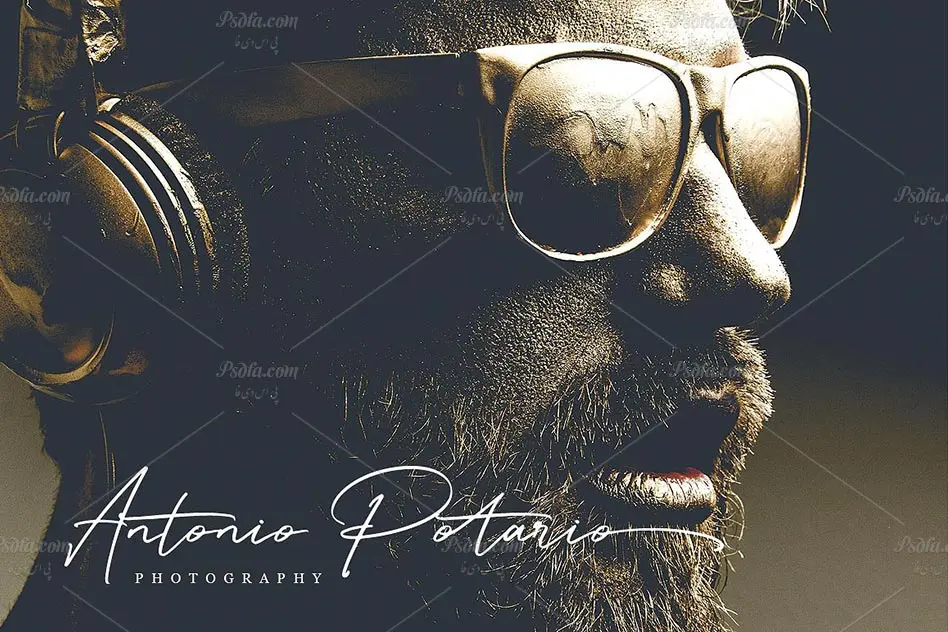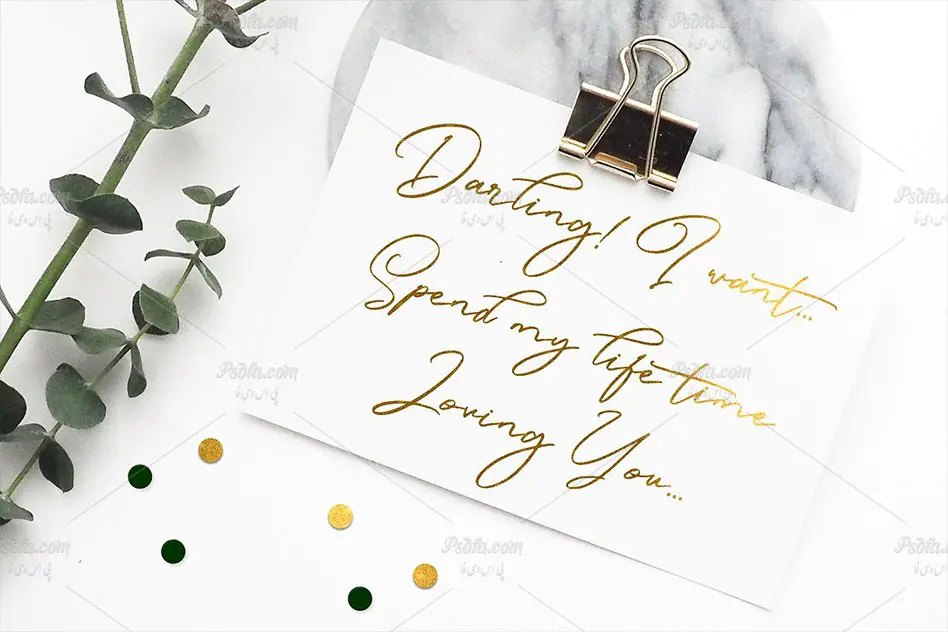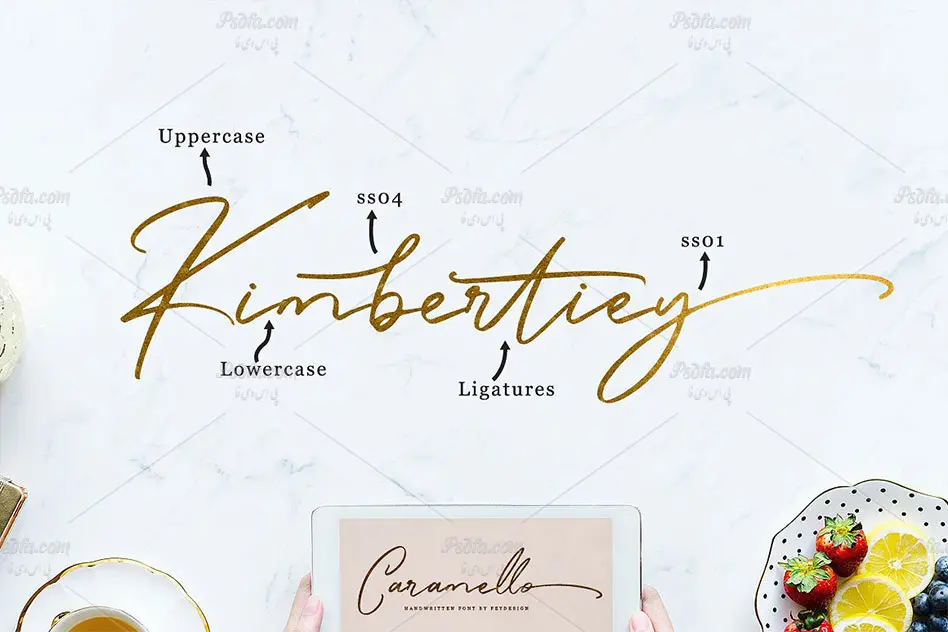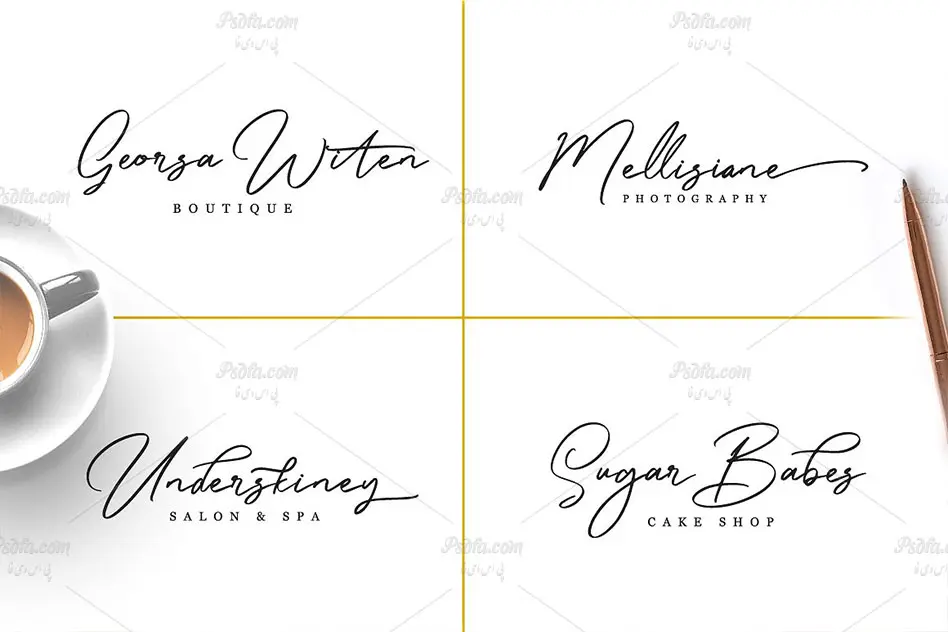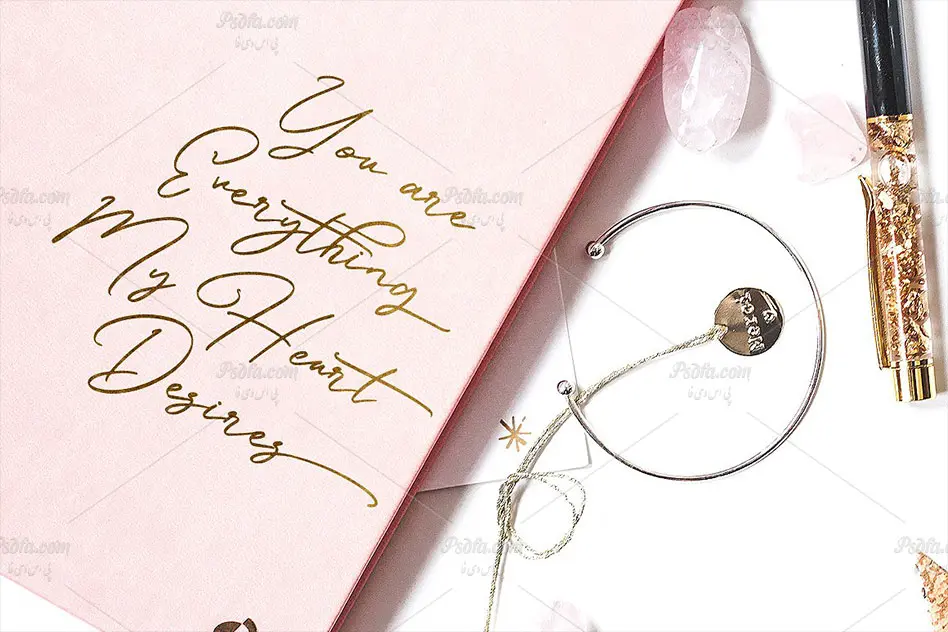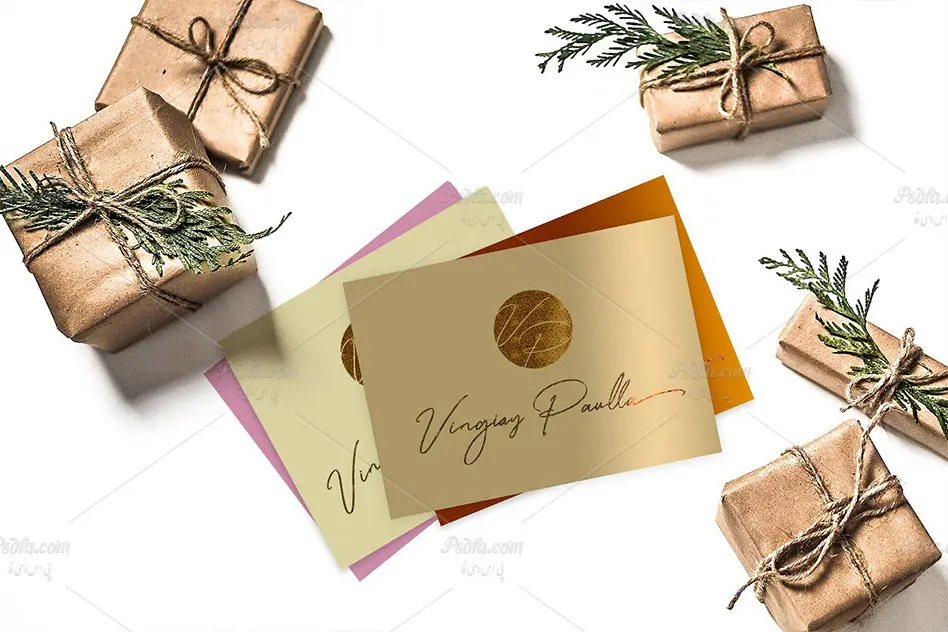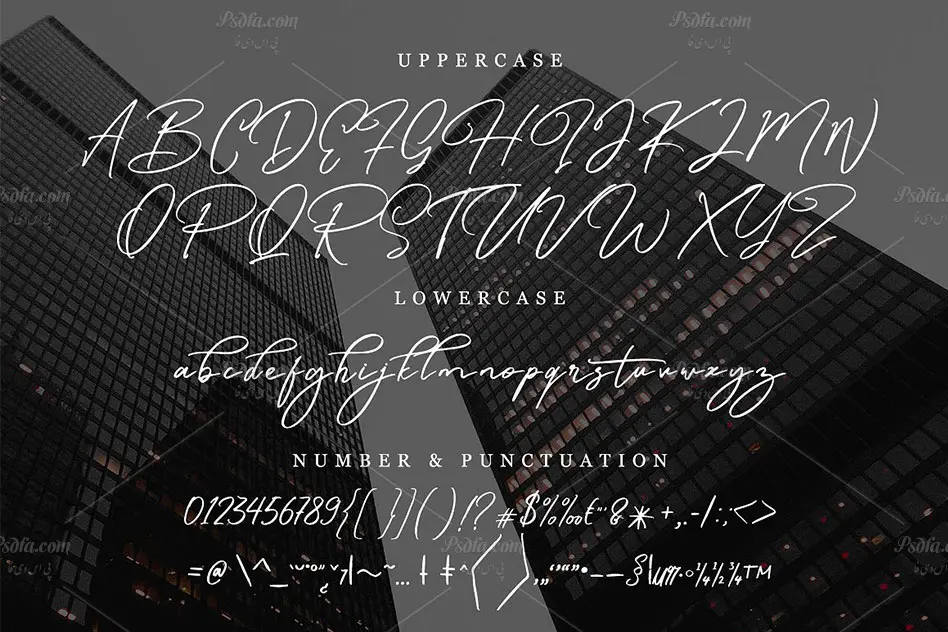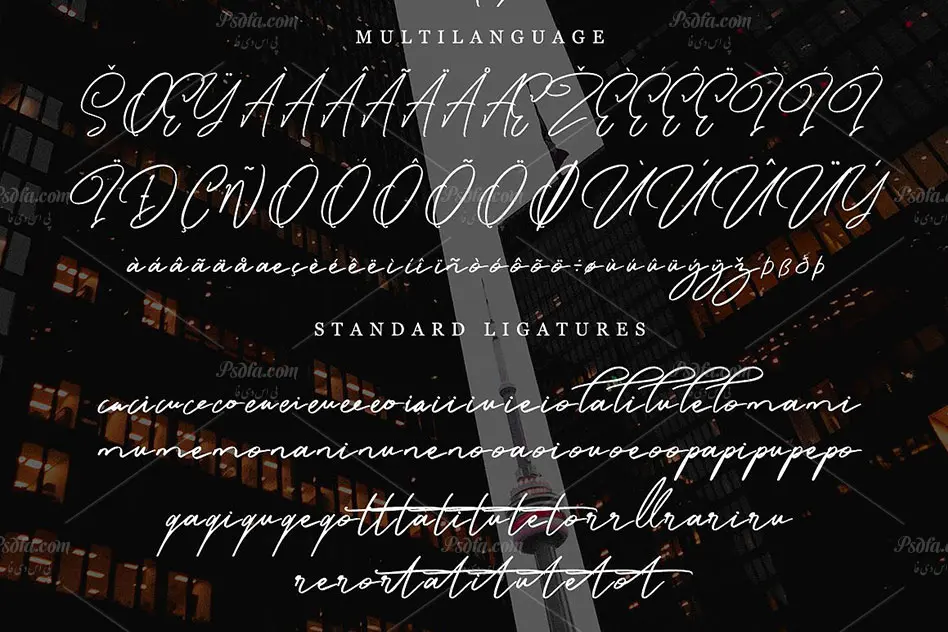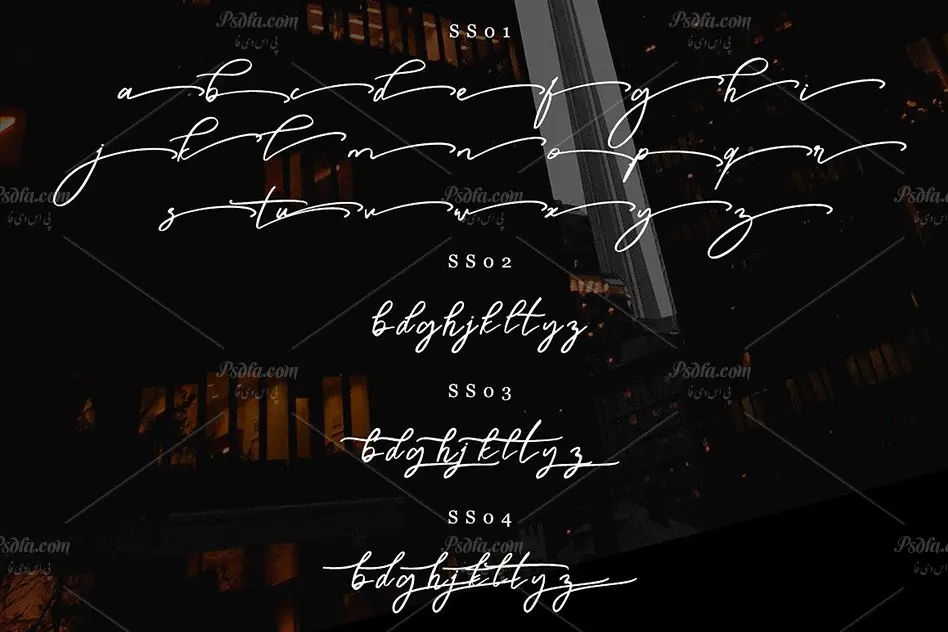
فونت انگلیسی دستنویس فوق العاده زیبای Caramello مناسب برای طراحی
در این قسمت از سایت شاهد فونت انگلیسی دستنویس فوق العاده زیبای Caramello مناسب جهت استفاده در طراحی و گرافیک می باشید. این فونت زیبا در قالب 2 فایل ttf و otf در سایت بارگذاری شده اند که پس از نصب یکی از این دو فایل در پوشه فونت های سیستم قادر به استفاده از آن در تمام نرم افزارهای گرافیکی و ویرایشگر متن از جمله نرم افزار فتوشاپ ، مجموعه نرم افزار آفیس و … خواهید بود. همچنین نسخه وب این فونت نیز با فرمت های woff و woff2 در فایل فشرده موجود بوده که از آن می توانید در طراحی صفحات وب استفاده کنید.